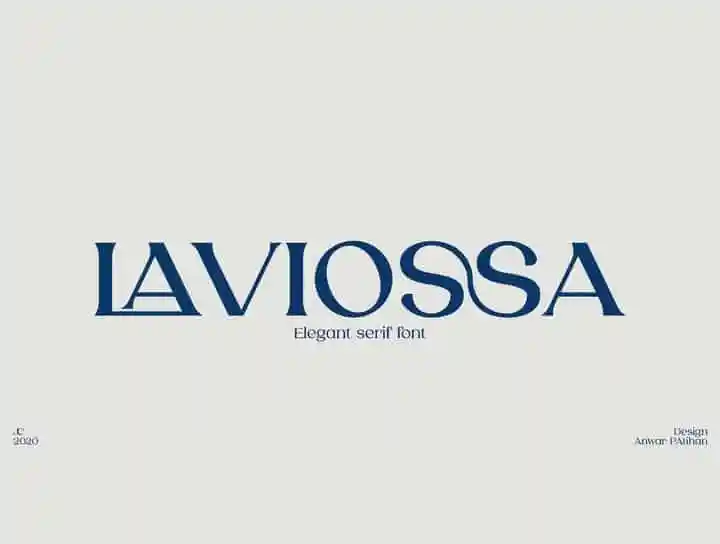
Laviossa Serif é uma elegante fonte gótica que se destaca por sua sofisticação e originalidade. Inspirada pelo trabalho criativo da Jehoo Creative, essa fonte moderna mantém um caráter suave e minimalista. As letras pequenas têm um toque distintivo que representa um vento flexível, enquanto suas curvas macias dão uma aparência forte a qualquer design. A Laviossa combina de forma harmônica com estilos simples e minimalistas, tornando-a perfeita para quem procura uma fonte sofisticada e única. Não importa qual estilo seu projeto tenha, a Laviossa Serif se destaca, garantindo que sua criação fique imediatamente acentuada e chamativa em qualquer ambiente de design.